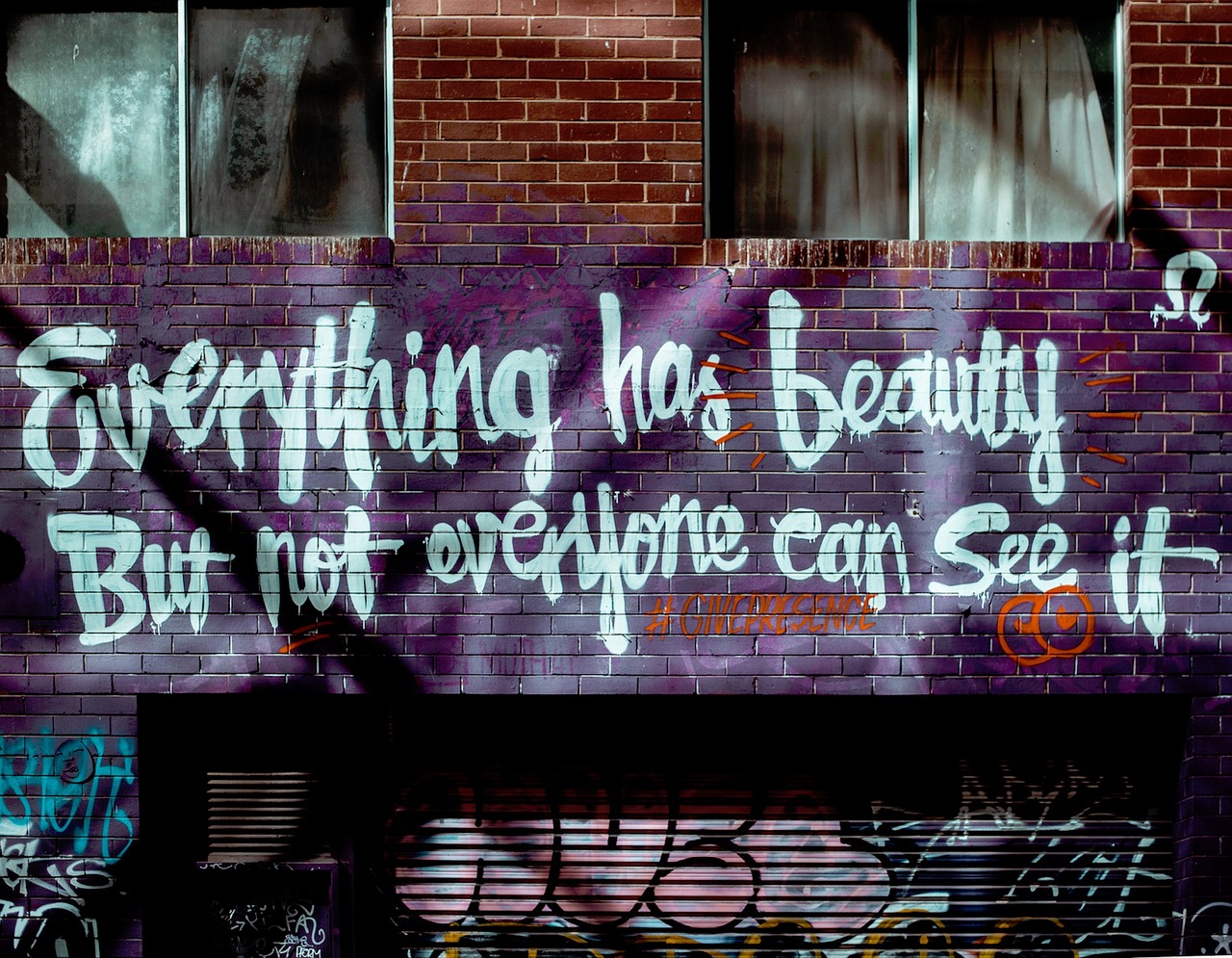
Quanto è affascinante quella cultura urbana, quella che trova la sua massima espressione nelle scritte e nelle opere d’arte sui muri e in giro per la città? Una volta le scritte sui muri erano considerate un atto vandalico, oggi la cultura urbana è una vera e propria corrente artistica che nasconde nel lettering elaborato dei graffiti tutta la sua vera anima. Ecco i font graffiti più belli da provare per entrare nel vivo di questa sub cultura.
La cultura urbana
Quello che un tempo veniva considerato un atto vandalico incarna oggi una cultura urbana che vuole lanciare un messaggio a supporto dei più deboli.
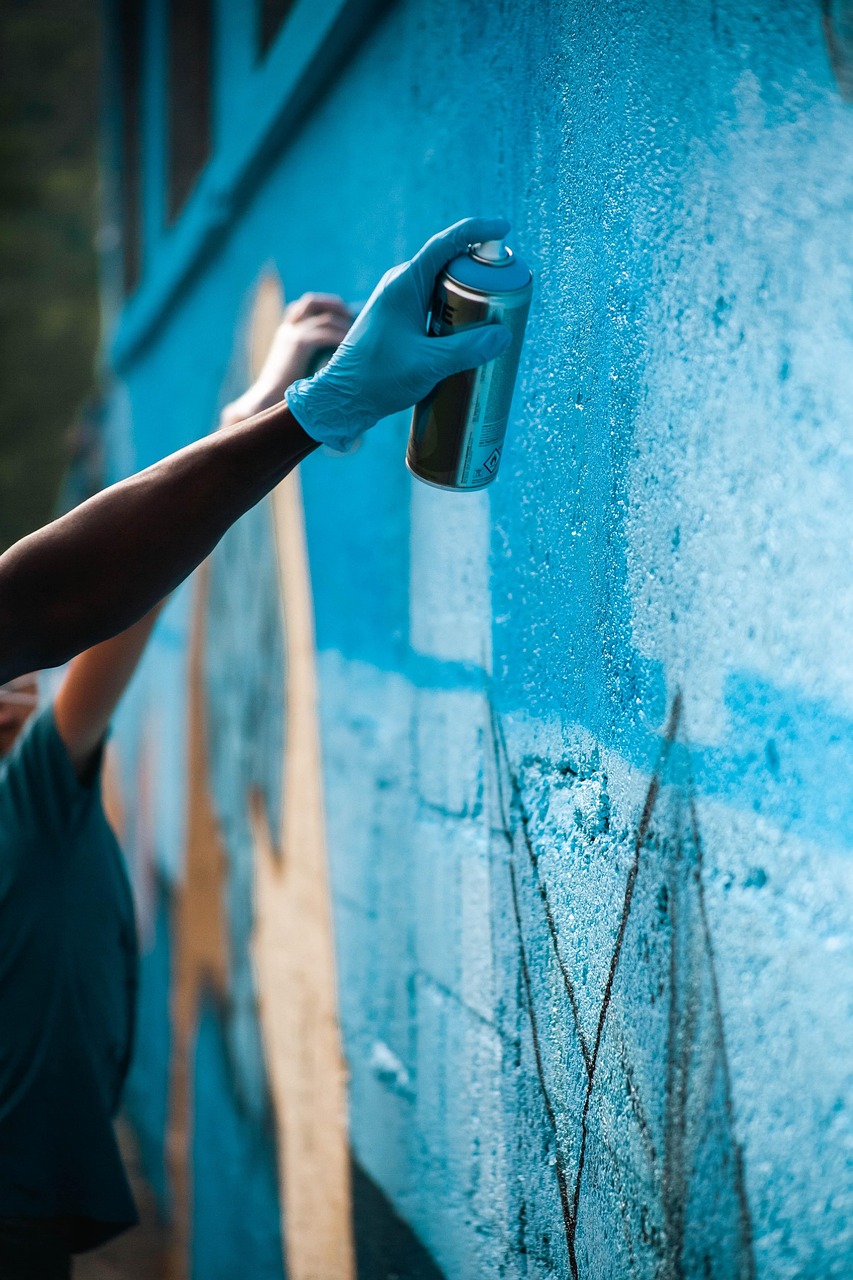
L’arte di strada è diventata una forma di comunicazione diffusa ed estremamente potente. Il principale elemento dell’arte di strada e della cultura urbana è proprio il lettering, impresso con bombolette spray.
I caratteri utilizzati sono originali, espressivi ed estremamente popolari.
Per capire quando i font graffiti sono nati dobbiamo tornare indietro alla nascita della cultura urbana, a New York, negli anni ’60 – ’70. La cultura nasce negli ambienti dell’hip-hop e dall’idea di occupare gli spazi urbani liberi.
Le sottoculture urbane sono in realtà un insieme di varie correnti che si influenzano tra di loro. L’arte dei graffiti, in particolar modo, è stata influenzata dal mondo dell’hip-hop e del rap, dello skate e della street wear.
Caratteristiche dei font graffiti
I font graffiti sono ribelli, creativi, espressivi e con una personalità esplosiva. Le forme sono irregolari e fluide, le linee possono essere sia morbide che spezzate.
L’idea è quella di ricordare la vernice spray e, in ogni caso, la scrittura a mano, veloce, disordinata, sporca. Le forme volutamente asimmetriche, perché la scrittura con lo spray è imprecisa e irregolare.
I colori utilizzati sono solitamente molto forti, le texture creano contrasti e sfumature vivaci, includendo segni di usura, gocce e colature di vernice.
Le tipologie possono variare molto e vanno da quelle con le lettere più morbide e tondeggiante e quelle più affilate e spigolose, includendo anche diversi stili 3D.
Font graffiti: Urban Heroes
Uno dei font più caratteristici di questa tipologia di caratteri è l’Urban Heroes. Questo font incarna perfettamente la cultura urbana, con i tratti audaci e i contorni fluidi.
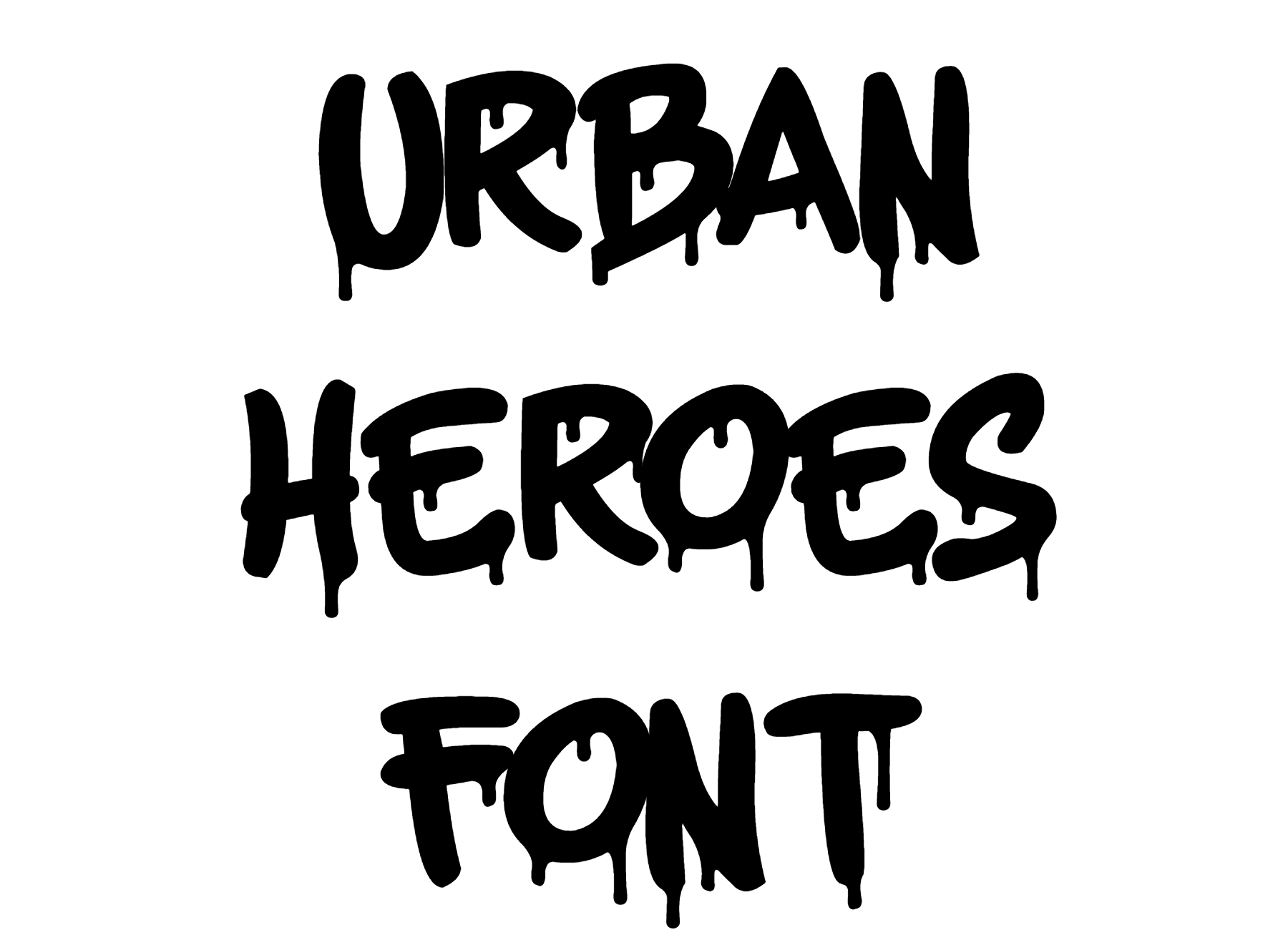
L’effetto è quello della bomboletta spray, con tanto di vernice colante. A differenza di altri font dello stesso stile questo è molto leggibile, ciò lo rende perfetto per essere utilizzato in molti contesti.
Decipher
Questo font è originale ed eccentrico. Molto diverso dal precedente e meno versatile e leggibile, ma sicuramente esprime una forte personalità ed energia.
I tratti delle lettere di questo carattere sono irregolari e i bordi spigolosi. Perfetto per catturare l’attenzione e per esprimere messaggi legati alla sub cultura urbana.
Font graffiti: Youth Regular
Questo font esprime tutta la forza della cultura urbana, grazie alle sue lettere ampie, piene e robuste. Le linee sono fluide e i tratti pieni, il design è forte e dinamico.
Youth Regular è perfetto per un pubblico giovane e ribelle.
Docallisme On Street
Questo è font tridimensionale, che molto bene si sposa con la cultura di strada. I tratti sono spessi e angolari e la profondità donata dal tridimensionale rende le lettere accattivanti ed energiche.
Può essere utilizzato per tutti i messaggi delle sub culture urbane, dalla street art al merchandising del mondo dello skate e dello streetwear.
Font graffiti: Most Wasted
Most Wasted è un font dinamico, vivace e movimentato. Non facilmente leggibile, ma sicuramente con una spiccata personalità.
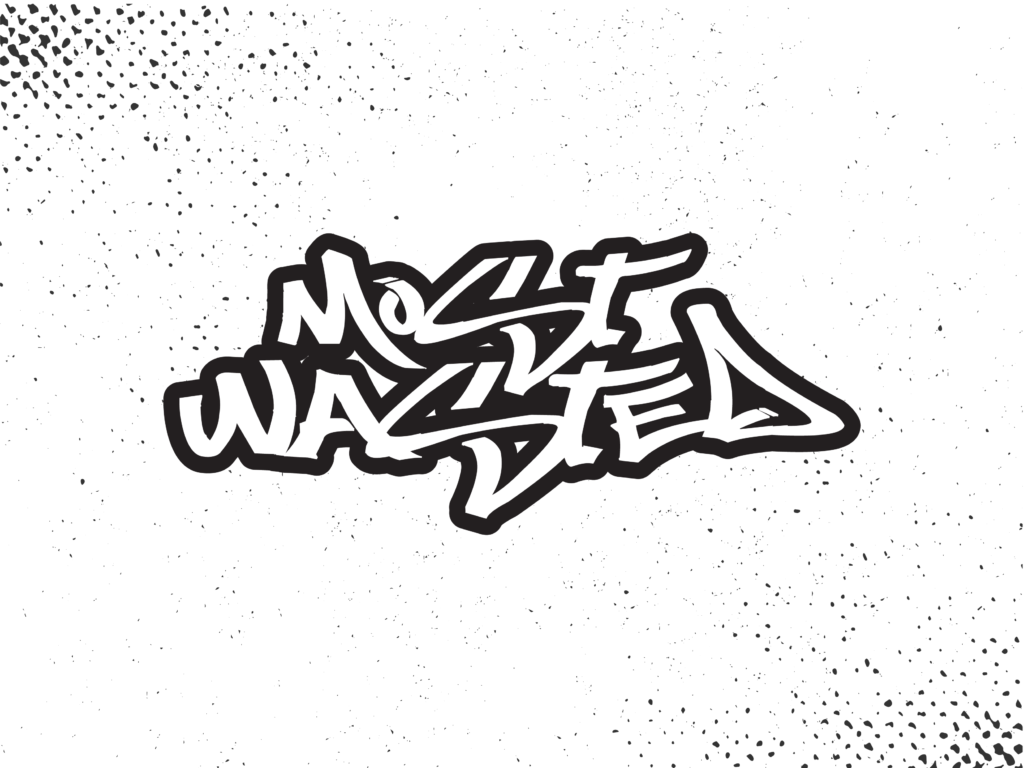
È perfetto per ricreare l’effetto dell’arte urbana e dei graffiti sui muri della città.